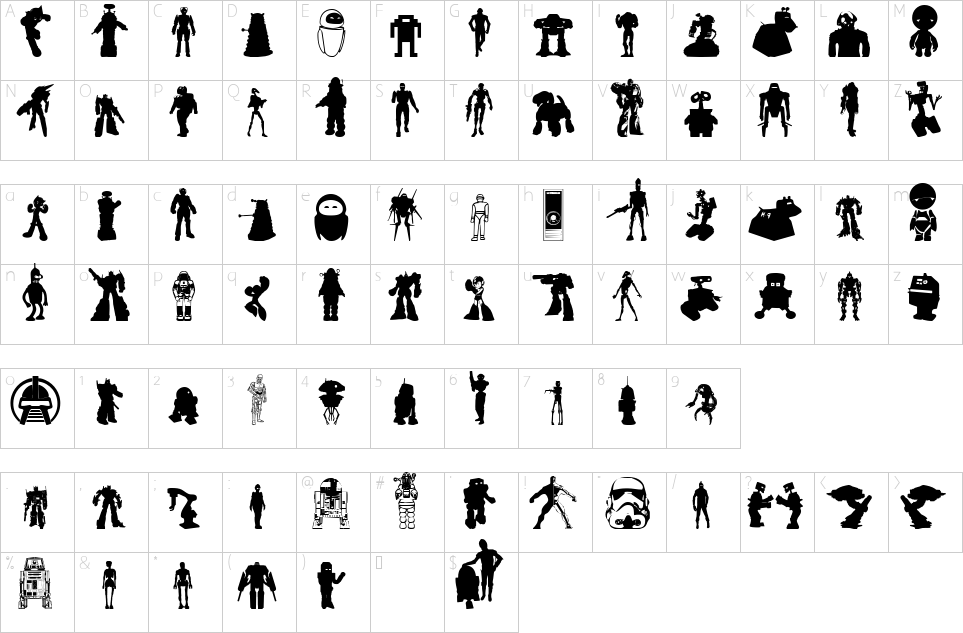
Look Sir Droids Font – Download Grátis
A fonte Look Sir Droids é uma criação moderna e atraente que se destaca entre as opções disponíveis para designer. Desenvolvida por Iconian Fonts, ela oferece um equilíbrio perfeito de personalidade e facilidade de uso, tornando-a ideal tanto para projetos digitais quanto impressos. Esta fonte gráfica foi concebida para proporcionar uma experiência visual única, com seus detalhes elaborados que adicionam profundidade a qualquer projeto. Com seu design criativo e elegante, ela é perfeita para aplicativos de negócios, materiais educacionais ou até mesmo para criações artísticas. Atualmente disponível em versões para Windows e Mac, Look Sir Droids foi descarregada por 37.869 vezes, uma indicação de sua popularidade entre criadores. Como fonte gratuita, ela oferece aos designers a oportunidade de experimentar algo novo sem custos adicionais. Se você está procurando por um recurso gráfico para adicionar ao seu arsenal de ferramentas de design, Look Sir Droids é um excelente escolha.